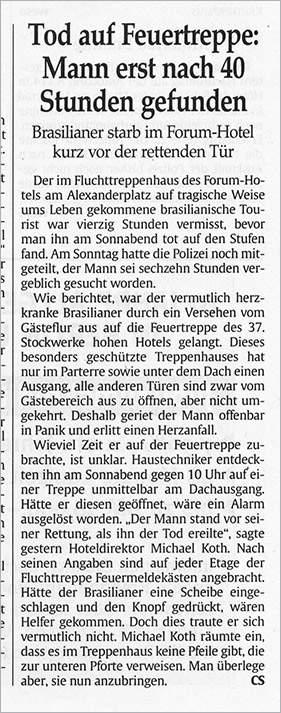
Lebensrettende PfeileKommunikationsdesign kann Leben retten. Daran erinnert mich eine Meldung
der Berliner Zeitung, die ich eben beim Aufräumen fand. Im Mai 2001
verirrte sich ein 69-jähriger Mann im Treppenhaus des Forum Hotel
(heute Park Inn). Die Meldung endet mit dem Satz:
»(Name) ... räumte ein, dass es im Treppenhaus keine Pfeile gibt,
die zur unteren Pforte verweisen. Man überlege aber, sie nun
anzubringen.«
![]() Vielleicht muss man den Sicherheitsverantwortlichen für solche
Gebäude einfach mal sagen, dass Kommunikationsdesigner weder Schildermaler
noch Hübschmacher sind. Es geht um mehr als um schöne Formen, manchmal
um Leben und Tod. Sicher gibt es ausreichend Vorschriften von technischen
Überwachungsvereinen. Aber Selbstnachdenken hat noch nie geschadet, und
Experten zu konsultieren erst recht nicht.
Das Notausgang/Fluchtweg-Piktogramm (oben) stammt aus der Leitsystem-Schrift FF Info Pict, die MetaDesign 1997 für den Flughafen Düsseldorf entwickelt hat. Ein Jahr zuvor kam es dort zu einem tragischen Brand. 1998 wurde das Sicherheitskonzept des Flughafens von der Stiftung Warentest mit der Bestnote ausgezeichnet. MetaDesign zum Leitsystem des Flughafen Düsseldorf Brand eins über Paul Mijksenaar und seine Ausschilderung des Flughafens Schiphol in Amsterdam Bilderstrecke zum Orientierungssystem des Flughafen Schiphol Zwischenstand zum Projekt gemeinsames Leitsystem für die New Yorker Flughäfen ![]() Meldung der Berliner Zeitung vom 14. Mai 2001, Online-Meldung dazu und vom Folgetag Herausgegeben: Do - August 18, 2005 at 03:36 nachm. | |